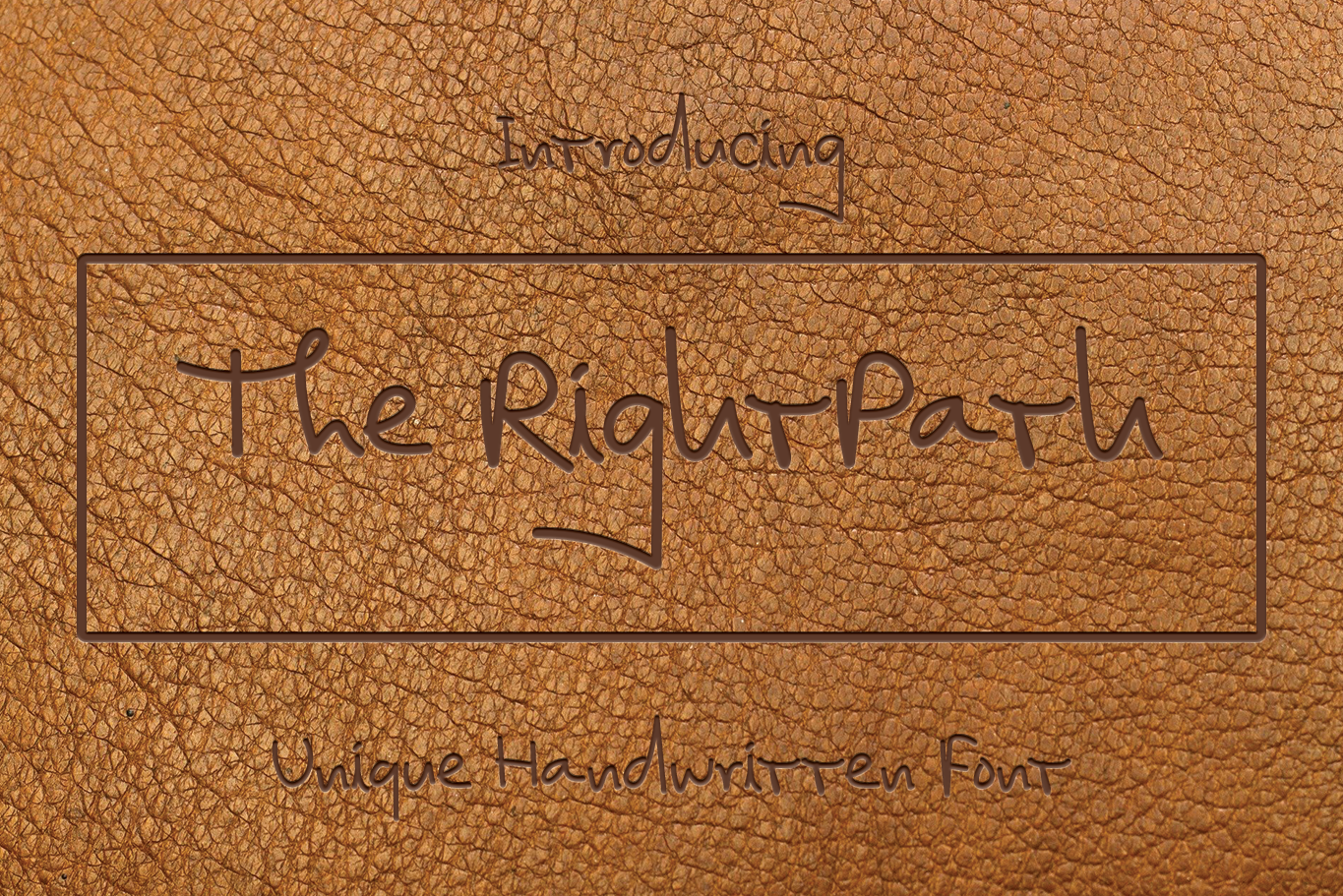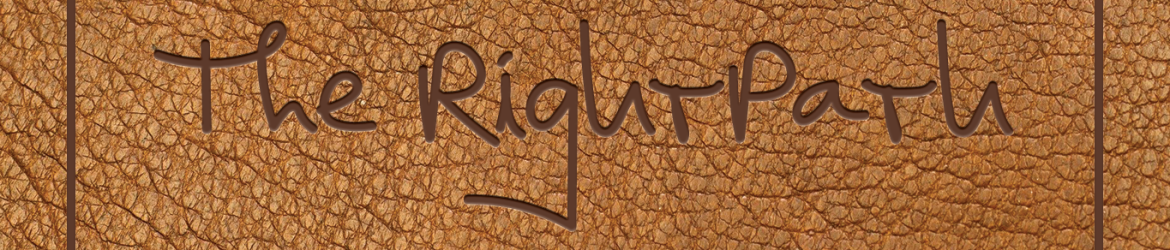
The RightPath Font – Download Grátis
A fonte “The RightPath” é uma escolha ideal para quem deseja adicionar personalidade a seus trabalhos sem comprometer o profissionalismo. Seu aspecto suave e simples faz dela uma opção perfeita para qualquer projeto que exija um toque de autenticidade e originalidade, seja em cartazes chulinhos ou materiais didáticos educacionais. Suas letras escritas à mão genuínas trazem a sensação realista necessária aos seus designs, proporcionando uma aparição natural e quente que enriquece seu trabalho. Para os amantes de projetos criativos e de design pessoal, “The RightPath” é um elemento indispensável no kit de ferramentas digitais do designer.